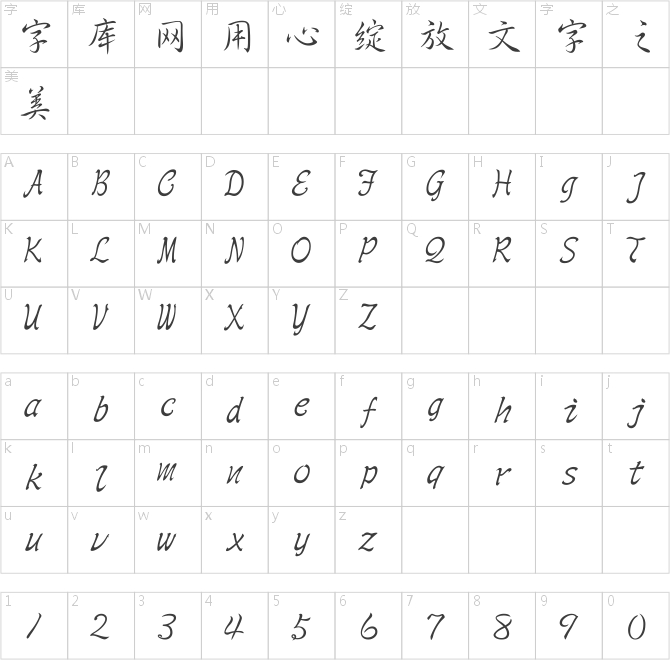
行書
文鼎
文鼎中行書簡體繁體合并形成,兼容新版win10
更新Power TrueType Version 5.0版,和原Power TrueType Version 4.0或Power TrueType Version 4.5版本相比又將原Power TrueType big5的擴展471個外字集的部分沒有映射字碼點的漢字進行了對號入座,并修復(fù)『?』字誤映射到『抝』字位置的錯誤。